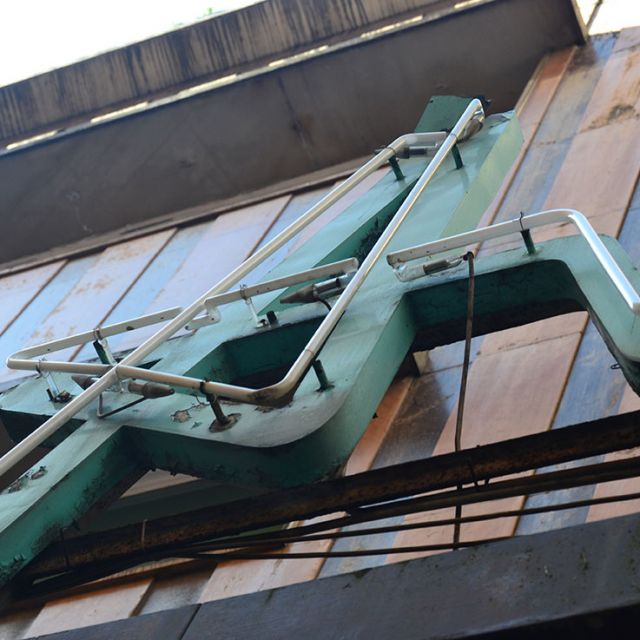
1957
[wyde_info_box title=»Tipografía» icon_set=»typicons» icon_typicons=»typcn typcn-sort-alphabetically»]Script[/wyde_info_box][wyde_info_box title=»Técnica» icon_set=»typicons» icon_typicons=»typcn typcn-brush»]Metal y Neón[/wyde_info_box]
Abierto en 1957, el característico rótulo que asoma está totalmente personalizado. Está basado en el propio trazo del fundador del mismo, Marcos Restegui, creando una tipografía única. En origen estaba colocado en sobre la propia fachada, al igual que «Cine». El nombre del cine está inspirado en el nombre de la mujer del fundador.
Actualmente sigue en activo, y se puede ver sus neones iluminado la noche de Santander.